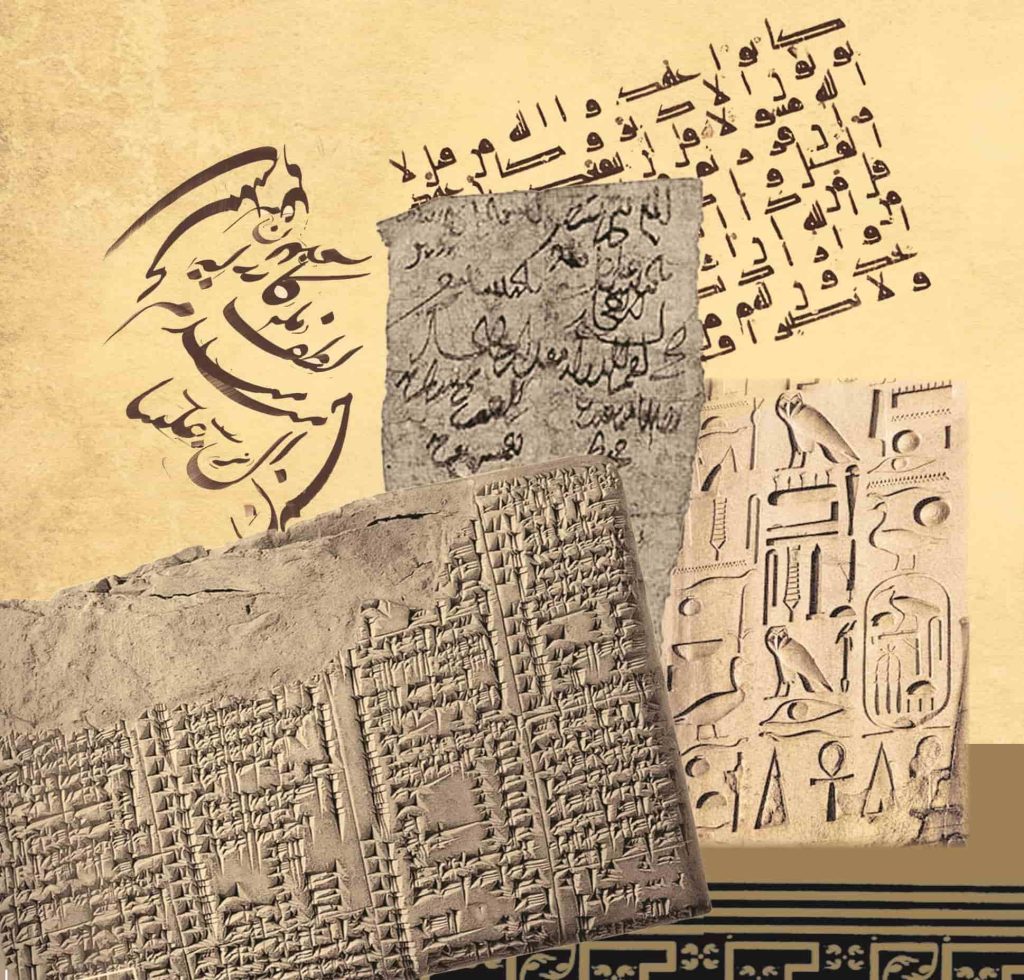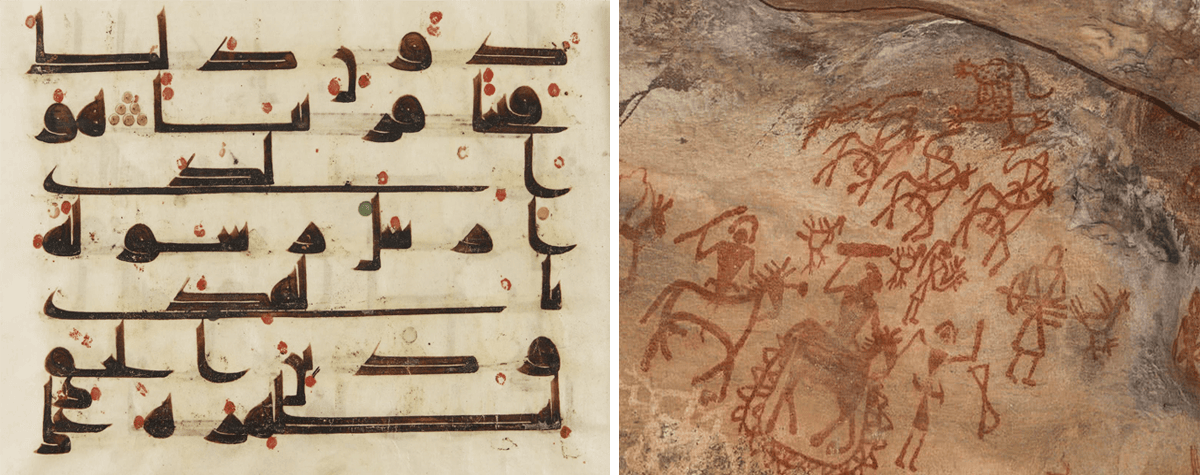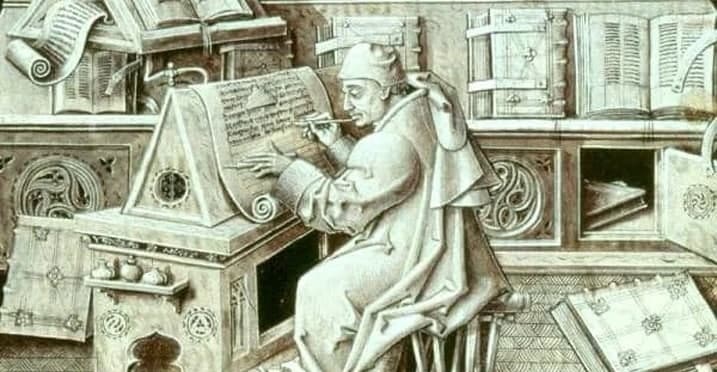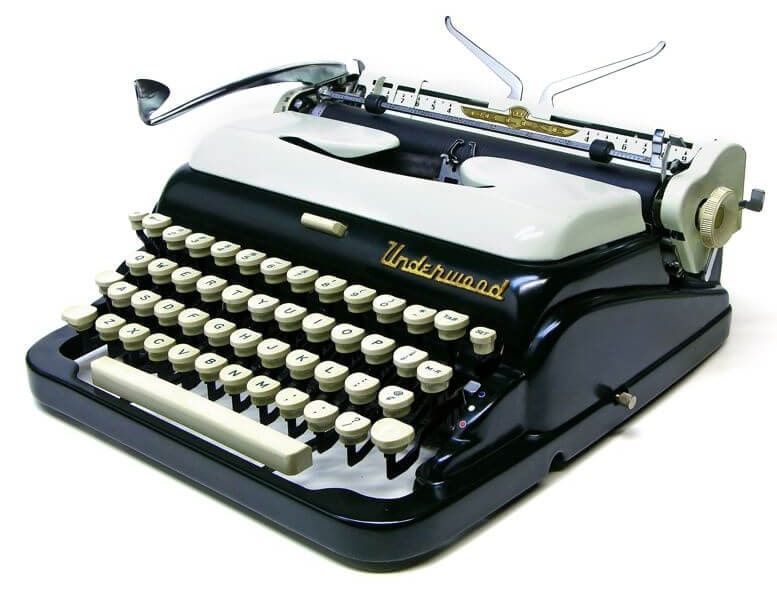
تاریخچه پیدایش خط | چطور انسان از خط به تایپ رسید
انسان موجودی اجتماعی است . جمله ای که از دوران مدرسه و درس به خاطر داریم همه ما آدمها نیاز به ارتباط گرفتن با یکدیگر به دلیل رفع نیاز های خودمون داریم. تاریخچه پیدایش خط یک مسیر به قدمت عمر بشره که همچنان ادامه داره و روز به روز این مسیر به رشد خودش ادامه میده. حتی همین زمانی که شما این مطلب رو دارین می خونین.
تاریخچه خط در زندگی انسان های نخستین
انسان های نخستین برای همون دلیل بالا یعنی رفع نیاز های خودشون مجبور به گرفتن ارتباط با هم نوع خودشون بودن. در ابتدای کار قراردادهای آوایی برای اشیاء پیرامون و هر چیزی که چشمشون می دید در نظر گرفتن مثلا به این حیوان درشت میگیم خرس ، به این گیاه میگیم گل و به همین ترتیب…
نخستین نگاره پیدایش خط
این روند ایجاد پروتکل و قرار داد ها به مرور تکمیل و پیچیده تر شد. بعد از قرار داد کلامی انسان ها شروع به قرارداد نوشتاری کردن به این معنی که علائم خاص یا اشکال و هرچیزی که خودشون در نظر می گرفتن رو به محیط پیرامونشون نسبت می دادن. مثلا شکل 8 رو واسه نشون دادن کوه و … از این مرحله دیگه تاریخچه پیدایش خط کم کم شروع خودش رو داشت استارت میزد.
خط های اولیه
پیدایش الفبا ، انقلابی در خط یا نوشتار
تا اینجا خط شکل گرفت البته در ابتدایی ترین شکل خودش . انسان روز به روز این مسیر رو توسعه میداد. با مرور زمان آدمها به جای نشون دادن هر چیزی با یک علامت گرافیکی یک قدم جلوتر رفتن و الفبا رو اختراع کردن. انسان ها به این نکته دقت کردن که همه  قراداد های کلامی که بین خودشون درست کرده بودن تشکیل شده جزء های آوایی مشترک مثلا خرس کوه آب آتش خاک و… واژه های مشترک بین کلمه ها رو فهمیدن.
خطوط ابتدایی بشر
البته ما انسان های عصر حاضر میدونیم که تمامی کلمات از حروف و آوای های اون درست میشن که در بیشتر زبان های دنیا زیر 50 حرف و آوا وجود داره. اینجا بود که خط های مختلف و حکاکی اون ها رو سنگ ها ظهور پیدا کرد . انسان های مختلف سراسر این کره خاکی در مناطق خودشون قراردادهای آوایی و نوشتاری خودشون رو روز به روز پیشرفت میدادن و قائده مند تر می کردن. به همین دلیل زبان ها و خطوط مختلف به همراه تاریخچه اونها در جهان امروز رو شاهد هستیم.
تاریخچه پیدایش خط
ظهور تایپ نقطه ای عطف در این مسیر
این مسیر همچنان رشد خودش برای هر زبان رو ادامه میداد تکمیل تر، قائده مند تر  .. تا اینکه انقلاب صنعت در جهان شکل گرفت. نقطه عطفی در تاریخچه خط و کلمه تایپ به فهرست واژگان بشر افزوده شد. هر کدام از حروف الفبا بوسیله حروف جابجا شونده و مهر های ماشینی ایجاد بشه که روند رو سریعتر انجام میده و تایپ دیزاینر ها این حروف جابجا شونده رو بر اساس ایده خودشون طراحی میکنن .
ماشین چاپ قدیمی